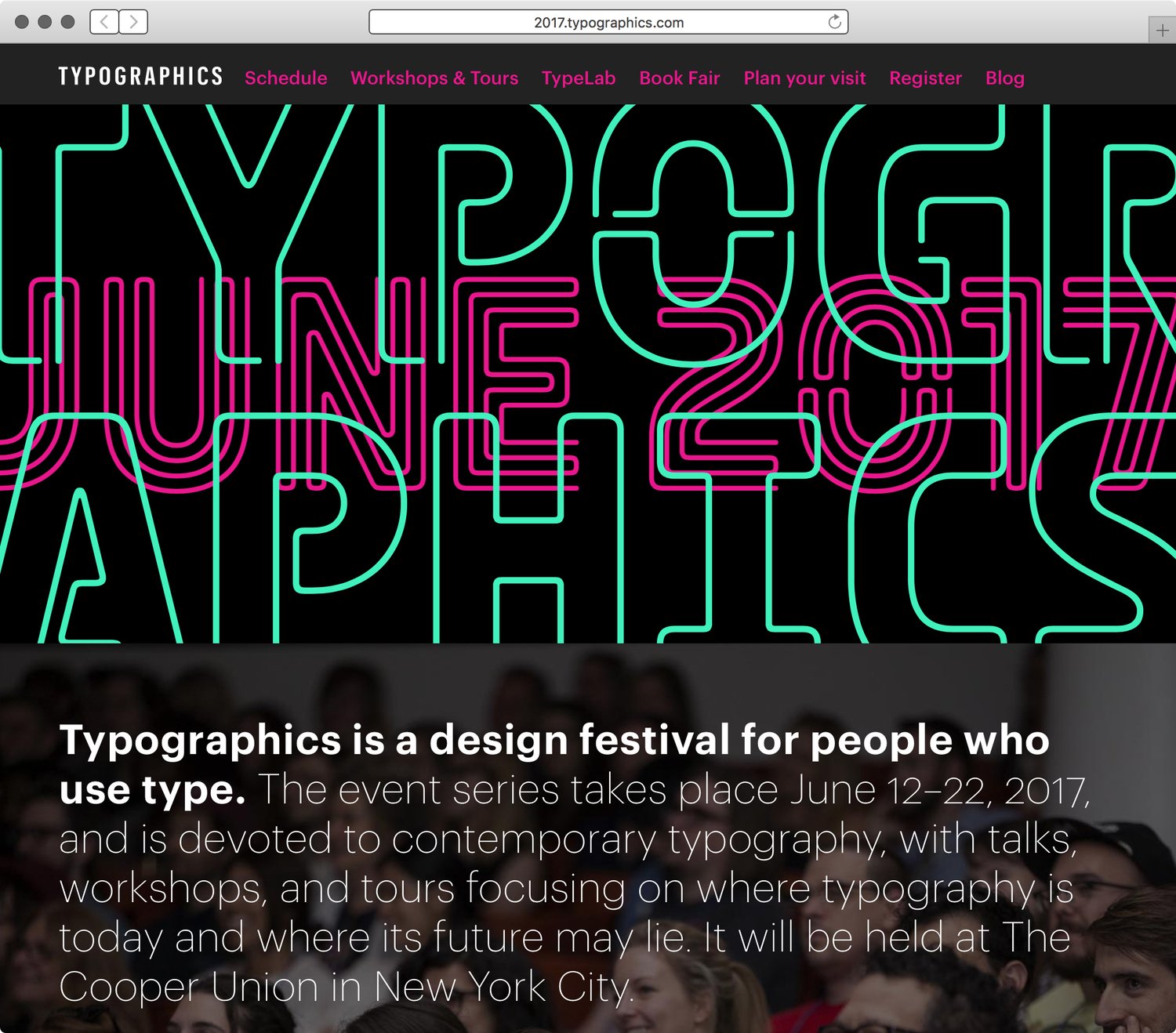
Илья Рудерман: Меня интересует всё, что вы можете сказать о текущем положении дел, о сегодняшних технологиях, о том, что вообще для вас означает «сегодня».
Ник Шерман: Сейчас я примерно половину рабочего времени уделяю веб-дизайну, а вторую половину — кастомному шрифтовому дизайну.
Дэвид Джонатан Росс: Думаю, у тебя, Ник, больше шрифтовых семейств, чем у меня, хотя это и неочевидно. Они попросту сейчас на разных этапах доработки.
НШ: Они не завершены. У меня есть длинный перечень гарнитур, которые достаточно проработаны, — настолько, что я могу использовать их в собственных целях и предлагать тем покупателям, которые хотят их опробовать; но торговать большинством из этих шрифтов в розницу, понимая, что они полностью не отшлифованы, мне было бы неловко.
Шрифт Ника Шермана Papanek
Шрифт Ника Шермана Margo
Шрифт Ника Шермана Flight Center Gothic
Шрифт Ника Шермана Forester
Шрифт Ника Шермана Strike
Шрифт Ника Шермана Kultur
ИР: Ясно. Но вы же следите за нашей профессией в течение долгого времени — так же как я, уже более десяти лет, верно? Что вы думаете о её современном состоянии?
НШ: Если говорить о «шрифте сегодня» в широком смысле, ответ во многом зависит от контекста. Но даже если ограничиться технологией, можно сказать, что наиболее современный, «сегодняшний» элемент мира шрифтов — это вариативные шрифты.
ИР: Или «завтрашний».
НШ: Да, в некоторых отношениях и завтрашний. Есть некоторые студии, где дело продвигается очень быстро.
ИР: Помню, несколько лет назад в одной из твоих лекций ты говорил об адаптивном веб-дизайне. Ты рассказывал об эксперименте Марко Дугонича (хорватский дизайнер и программист. — Прим. ред.), когда размер шрифта менялся в зависимости от того, близко или далеко от монитора находится пользователь. Когда я увидел презентацию вариативных шрифтов, первое, что пришло мне на ум, был адаптивный дизайн. Я сказал себе: «Ну вот, мы это сделали. И уже получили образцы прекрасного интерфейса. Принцип адаптации к пользователю уже изобретён».
НШ: Я начал писать об этом несколько лет назад, публикуя мои статьи на A List Apart. Вначале я думал, что нас ждёт какой-то промежуточный период, когда начнутся попытки взлома со стороны тех, кто хочет заполучить материал ещё до появления официальной спецификации. Но тут объявили о вариативных шрифтах формата OpenType, и я подумал: «Отлично, мы можем обойтись без уродливого переходного периода». По-моему, это действительно классная работа. Меня всегда интересовало, каким будет шрифт завтрашнего дня.
ИР: HTML и всё вокруг этого формата, так?
НШ: Да, когда веб-шрифты только начинали входить в повестку дня, я уже интересовался ими всерьёз. А теперь стали реальностью вариативные шрифты, и перед нами открываются действительно увлекательные возможности. Но «шрифт сегодня» в плане открывающихся возможностей и «шрифт сегодня» в плане того, что популярно или наиболее значимо для мейнстримной практики прямо сейчас, — это не одно и то же.
ИР: Да, верно. Думая о завтрашнем дне с точки зрения технологии, мы вообще-то ожидали, что веб-шрифты станут популярны, но полной уверенности не было ни у кого. Они были чем-то вроде забавы для дизайнеров и разработчиков. Рынок всегда стремился контролировать разработку шрифтов. И с этим, насколько помню, было сопряжено немало проблем. Некоторые люди, особенно из ультраконсервативных шрифтовых бюро, опасались остаться без спроса на свои шрифты онлайн.
НШ: Да, но в большинстве этих бюро всё-таки поняли, что если кто-то хочет получить что-то в онлайне, то, скорее всего, он это так или иначе добудет.
ИР: Я знаю несколько сайтов шрифтовых магазинов, где можно целиком загрузить коллекцию шрифтов прямо с главной страницы.
НШ: Часто можно перейти на пиратский сайт раздачи файлов и сделать то же самое.
ИР: Да, это уже не проблема.
НШ: Стандарты явно эволюционируют. Очень долго — в течение десяти лет или даже больше — шрифтовая технология и схемы лицензирования оставались в основном одними и теми же. Все привыкли к такому положению дел и к тому, как всё это работает. Начиная с 1990-х годов нам никогда не приходилось обсуждать проблемы изменения шрифтовых форматов, и это было для всех очень удобно. Используемая в наших компьютерах операционная система могла меняться каждый год, мобильные устройства могли меняться постоянно — но наши шрифты всегда функционировали одинаково. Теперь, с появлением веб-шрифтов, и особенно вариативных шрифтов, мы оказываемся в другой ситуации. Новая технология меняет общую картину. Возникают возможности, которых не было раньше, и в этих условиях дизайнеры могут использовать шрифт иначе.
Шрифт Ника Шермана Sketler
ИР: Вы считаете, есть какая-то необходимость в новом шрифтовом формате? Я имею в виду не OTF, а нечто принципиально новое, с другими возможностями, с другой логикой?
НШ: По этому вопросу моя точка зрения крайне пристрастна, ведь шрифтовой дизайн и графический дизайн, которыми занимаюсь я, целиком опираются на латиницу. OpenType нельзя назвать идеальным форматом, но он отлично работает для дизайна латинских шрифтов. А вот со шрифтами типа арабского его возможности куда более ограниченные. Можно вообразить и нечто лучшее, в меньшей степени зависимое от наших глифов, которые нераздельно связаны с прямоугольниками. В основе этой зависимости от прямоугольников лежит история материальной технологии, которая сегодня уже не имеет прежнего значения и нередко становится обузой. Несомненно, тут может возникнуть масса интересных задач, даже и в контексте латинских шрифтов. По-моему, в известных пределах, из которых лично я не выхожу, OpenType — прекрасный формат, но это явно не последний шрифтовой формат, созданный человеком. И я очень часто задумываюсь: а что же появится после OpenType? Мы более тридцати лет использовали для рисования шрифтовых форм кривые Безье. Ждать ли изменений здесь? Начнём ли мы со временем использовать иной метод для рисования кривой, рисования криволинейных контуров?
ДДР: Да, это был пример постоянного обмена мнениями. Ты мог мне тогда сказать: «Слушай, было бы круто добавить сюда что-то в духе Георга Трампа или что-то броское».
ИР: Совсем другой способ тестирования гарнитуры. Проверять, как она работает онлайн, а не в печатном виде.
НШ: Сейчас в работе над шрифтовым дизайном я продвигаюсь очень быстро. Иногда вообще опускаю этап печатных проб и ограничиваюсь проверкой в HTML и CSS.
ДДР: У меня в настоящий момент нет принтера.
НШ: У меня тоже.